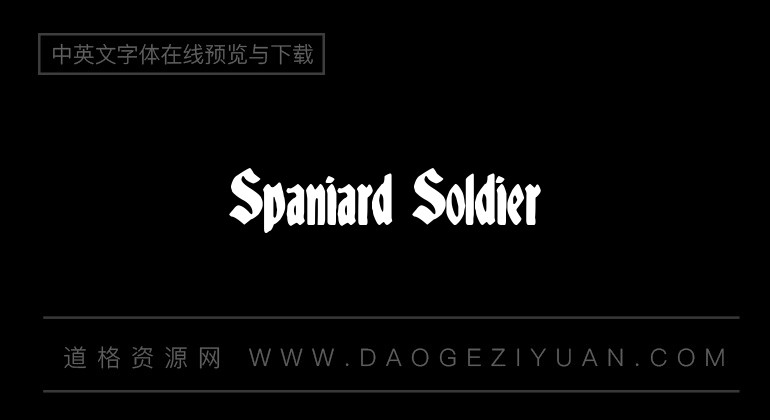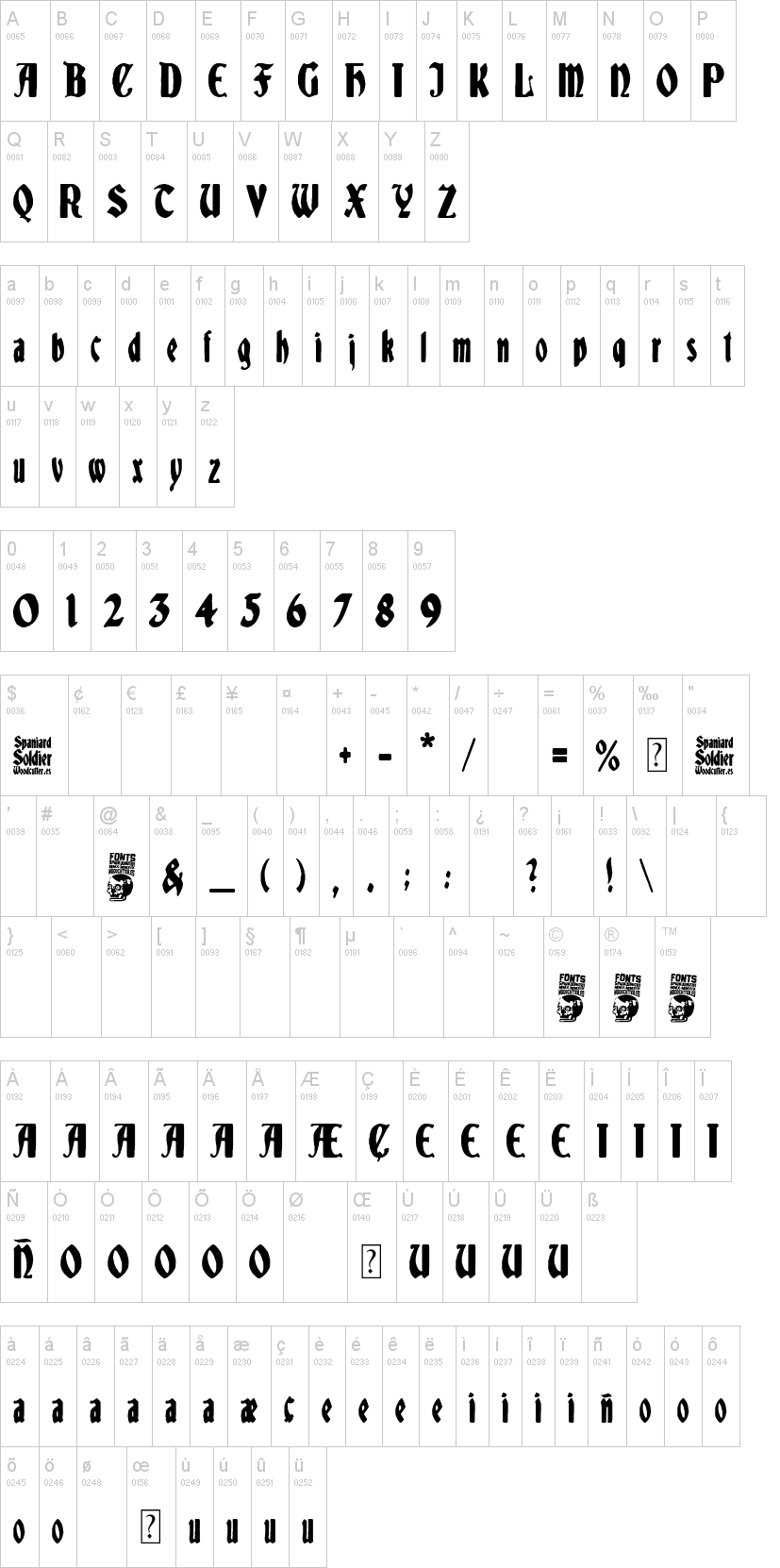
Spaniard Soldier
Spaniard Soldier是一款拥有特殊的西班牙风格的字体,其字体风格具有独特的古典复古风格。它的字体特点是大小写字母和数字的风格都是比较粗犷的,字体有一种古老的气息,可以表达出一种古老的历史感,而且字体的细节也非常精细,可以给设计师提供更多的灵活性。Spaniard Soldier字体适合用在海报、书籍、杂志和网页等设计上。
Spaniard Soldier是一款非常不错的手写艺术字体,具有很好的视觉感,适合于文化类的宣传设计、商业类品牌的广告和产品包装设计以及个性化文字排版等较多场景。